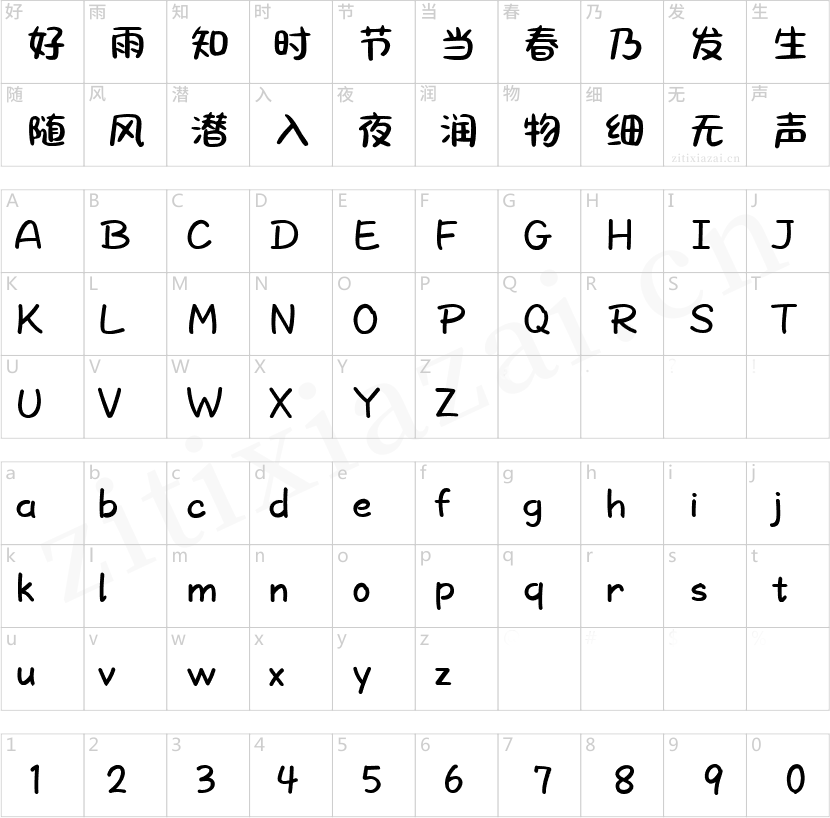
爱是偷偷藏不住呀
爱是偷偷藏不住呀字体
爱是偷偷藏不住呀是一款非常具有艺术性的字体,它的设计灵感来源于对古典艺术的研究,同时又融入了现代字体设计的元素。字形优美,笔画粗细变化自然,给人以大气、典雅的感觉。爱是偷偷藏不住呀是一款既传统又现代的字体,它的设计充满艺术感,美观大方,实用性也非常强。无论是对于设计师还是对于普通读者来说,都是一种非常不错的字体选择。爱是偷偷藏不住呀适合用于具有艺术感的场合,比如海报、宣传单张、书籍封面等。由于其字形流畅且具有动态感,也适合用于大量的文本排版,如报纸、杂志等。